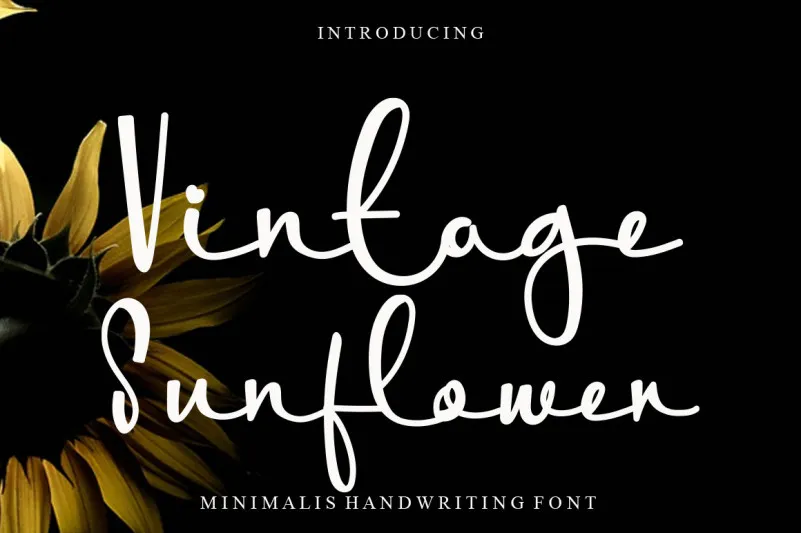
Vintage Sunflower Font – Fonte Grátis
Vintage Sunflower Font
Esta é uma fonte escrita a mão, com características encantadoras que se destacam por sua fluida e elegante curvatura. Perfeita para seus trabalhos mais refinados e singelos, essa fonte será um ótimo complemento para qualquer projeto que deseje exibir sutileza e delicadeza. A designer LevinCreative trouxe uma sensação de serenidade e harmonia à sua criação, tornando-a ideal tanto para textos como gráficos visuais. Ideal para trabalhos de design gráfico ou arte digital, essa fonte escrita a mão é certamente um elemento que enriquecerá seu projeto.